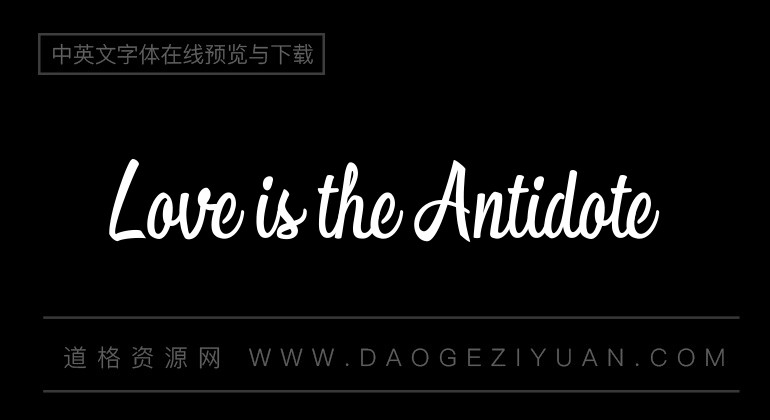
Love is the Antidote
很抱歉,作为一个语言模型,我没有办法直接展示字体的外观和样式。不过,我可以告诉你一些关于“Love is the Antidote”字体的信息。 “Love is the Antidote”是一种手写字体,它的笔画看起来很自然、流畅而且有点草书的感觉。这种字体的设计理念是让每个字母看起来像是由一个人手写的,这种效果给人一种亲切和自然的感觉。这种字体通常被视为一种温馨、友好和自然的字体,常常用于传达情感和个性化的信息。
Love is the Antidote是一款非常不错的手写艺术字体,具有很好的视觉感,适合于文化类的宣传设计、商业类品牌的广告和产品包装设计以及个性化文字排版等较多场景。